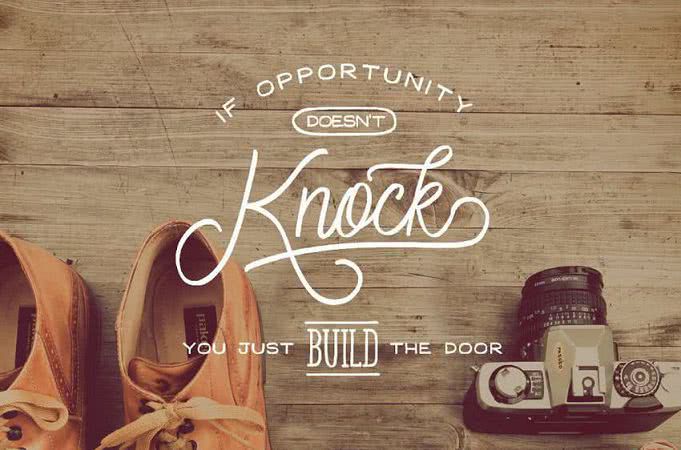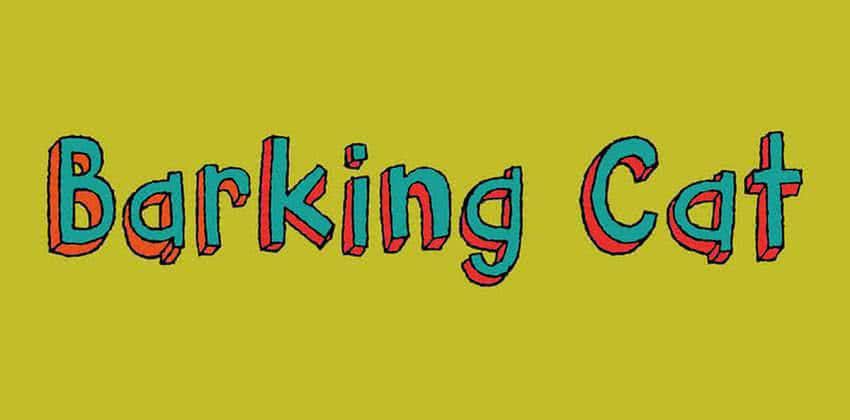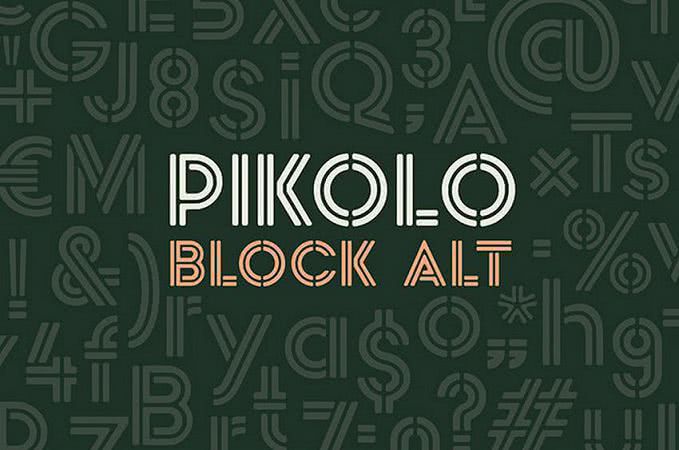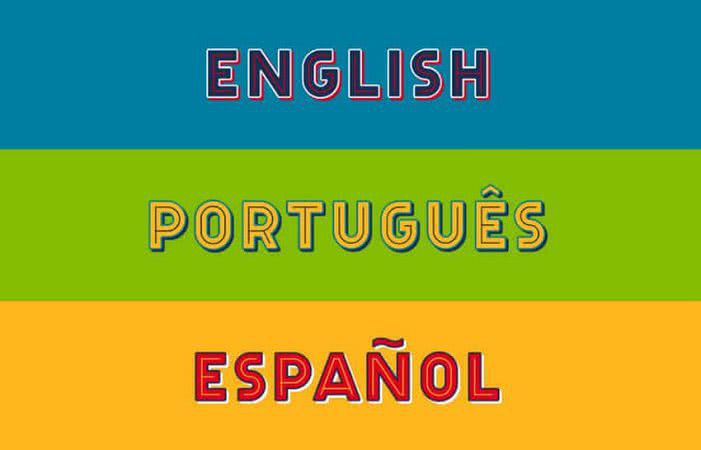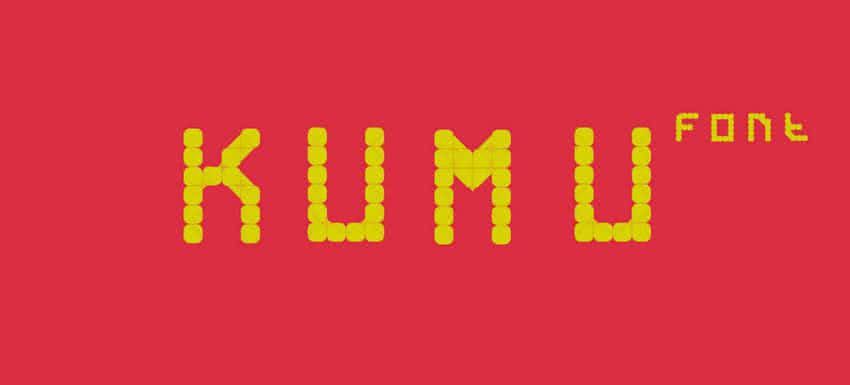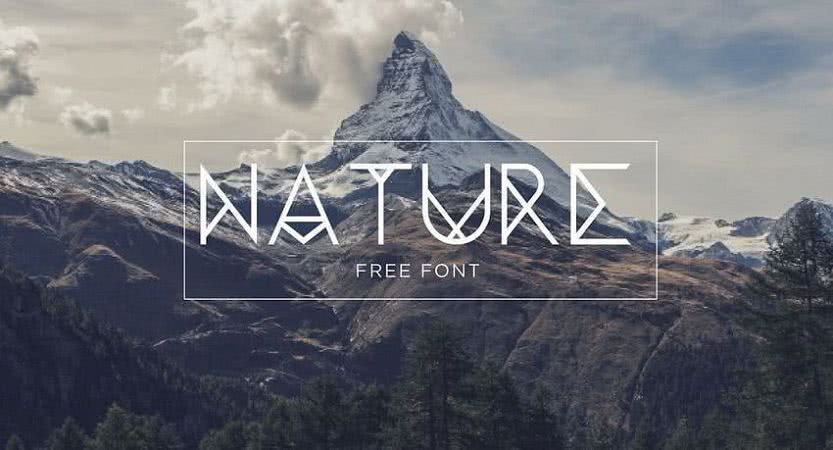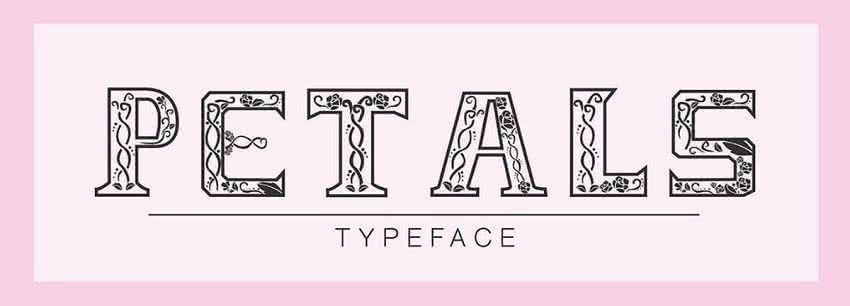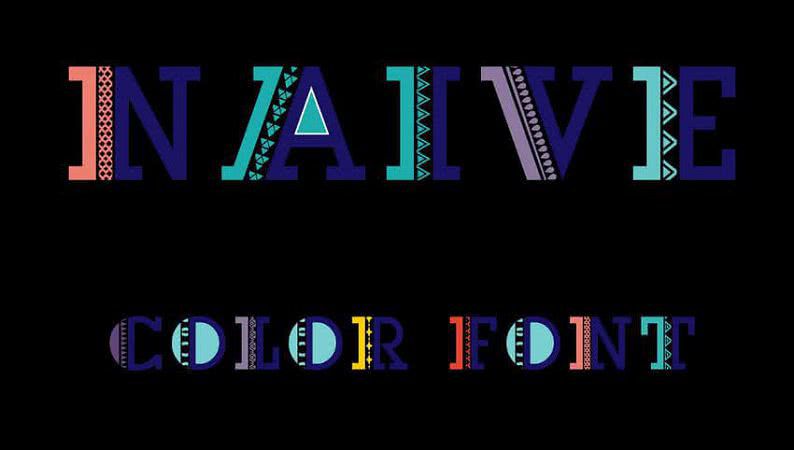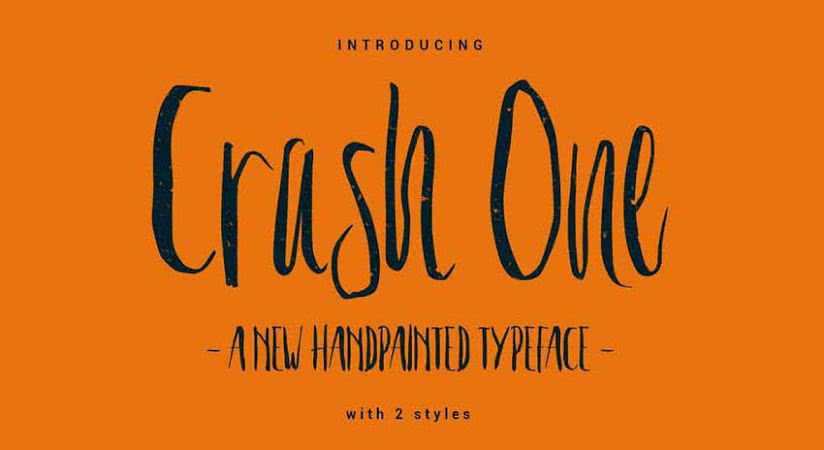
Картинка стоит тысячи слов. Мы все знаем, что изображение может быть очень описательным, но, нравится нам это или нет, мы не можем создавать дизайн без текста. Только с помощью слов мы можем быть уверены, что читатели получат точное сообщение. Это не означает, что мы прилипли к простому тексту; современные шрифты позволяют превратить простую надпись в произведения искусства.
Предположим, что вам нужно создать логотип в винтажном стиле; попробуйте старинный шрифт, такой как Vhiena, который включает в себя семь стилей для смешивания и соответствия. Или, может быть, вас попросили воссоздать ультрасовременную атмосферу, тогда вы можете сделать это с помощью шрифта, такого как Quantum, который имеет заглавные буквы с футуристической привлекательностью.
Vhiena
Quantum
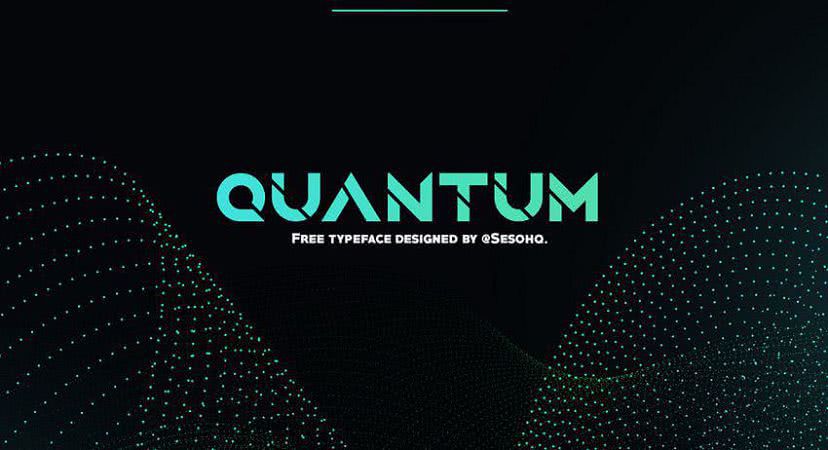
Нынешнее состояние типографики очень перспективно. От элегантных каллиграфических шрифтов, таких как SPIRITED FONT SET, до деревенских, таких как Barking Cat, шрифты могут быть всех форм, стилей и дизайнов.
SPIRITED FONT SET
Barking Cat
Разнообразие стилей поистине впечатляет. В то время как премиум-категория богаче, чем бесплатные шрифты, количество вариантов может вас удивить.
Учитывая современные тенденции, художники-типографики дарят нам новые решения. Пока что 2018 год находится под эгидой геометрии и высокотехнологичной атмосферы. Если вы хотите следовать тенденциям, вы должны обратить внимание на Pikolo Block Alt, Celebration, Kumu и Nature — эти бесплатные шрифты прекрасно справляются с этой задачей.
Pikolo Block Alt и Celebration — это два шрифта, которые имеют много общего. Они получают свою красоту из линейного искусства. Оба имеют заглавные и строчные буквы, цифры, символы и общие стилистические лигатуры. Используйте их для создания логотипов, заголовков или баннеров.
Pikolo Block Alt
Celebration
Каждый символ в Kumu — это гармоничное сочетание относительно больших точек. Шрифт выглядит немного деревенским, но он идеально подходит для восполнения брутальных проектов. Он охватывает общий набор символов.
Kumu
В отличие от предыдущих примеров, Nature умело сочетает геометрические детали и элегантные формы букв, что приводит к великолепному, изысканному шрифту. Его харизма идеально подходит для современного дизайна. Он состоит из заглавных и строчных букв и цифр.
Nature
Если вас не интересуют тенденции, вы всегда можете попробовать художественные или оригинальные решения. В нашем списке есть несколько шрифтов, которые придадут вашему дизайну индивидуальности.
Художественные шрифты
Художественные шрифты предназначены для добавления харизмы и творческой атмосферы. Рассмотрим Petals, Naive Color Font и Crash One.
Название шрифта Petals говорит само за себя. Он инкрустирован красивыми розовыми деталями, которые обеспечивают каждому символу прекрасную женскую ауру.
Petals
Naive Color Font — дерзкий, запоминающийся и эксцентричный. Его геометрическая атмосфера приятно подавляющая. Его можно использовать только для отображения заглавных букв, цифр и основной пунктуации.
Naive Color Font
Crash One — веселый и причудливый. С аутентичными кривыми рукописных форм он источает игривую харизму. Он состоит из всех распространенных букв, цифр, лигатур и знаков препинания.
Crash One
Оригинальные шрифты
Оригинальные шрифты идут рука об руку с художественными с одним небольшим отличием – они предпочитают держаться подальше от проторенной дорожки. Будучи смельчаками, эти экспериментальные шрифты удивляют своим необычным внешним видом. Рассмотрим два интересных примера: Fixer и Hawaiian Kids. Fixer — это универсальная многослойная система шрифтов, которая включает в себя семь стилей, которые вы можете комбинировать любым способом.
Fixer
Что касается Hawaiian Kids, первое, что приходит на ум, когда вы видите это: «Кто живет в ананасе на дне океана?» Вдохновленный любимым мультсериалом Nickelodeon про Губку Боба, шрифт выглядит комичным и веселым
Hawaiian Kids
Веб-Шрифты
Три стипендиата из W3C разработали WOFF (Web Open Font Format) в 2009 году, что делает его знаковым годом для веб-дизайна. WOFF изменил наше видение типографики для веб-сайтов, включая возможности использования необычных шрифтов. Рассмотрим Coral Reef Font. Этот шрифт идеально подходит для различных печатных проектов. Поставляется в WOFF, его можно легко использовать в веб-приложениях и он отлично смотреться на разных устройствах.
Coral Reef Font
Еще одна интересная вещь заключается в том, что есть множество конвертеров, которые позволяют использовать любой шрифт, например, Coco. Этот красивый шрифт имеет тонкие формы букв и доступен в стандартном OTF. Он идеально подходит для элегантного дизайна.
Coco
Последнее, но не менее важные: PSD и Wireframe шрифты
Эти два типа шрифтов не похожи на другие. Они особенные. Шрифты PSD невероятно творческие, а шрифты wireframe слишком упрощены.
Первый служит декоративным инструментом для преобразования регулярных заголовков в произведения искусства. Есть только один незначительный недостаток: нужно составлять буквы символ за символом. PSD шрифт Bright Calligraphy, Neon and Adan Font являются тремя представителями этого вида. Давайте взглянем на них поближе.
В шрифте Глеба Гуральника есть слияние металлического чувства и элегантная каллиграфия, которая приводит к выдающемуся шрифту. Набор состоит из 81 символа, охватывающего прописные и строчные буквы, цифры и знаки препинания. Каждый имеет свой собственный слой.
Bright Calligraphy
Neon выглядит урбанистическим и игривым. Стеклянные и блестящие поверхности с похожими на щетку штрихами и великолепной расцветкой формируют красивый шрифт, который идеален для показа табличек или лозунгов. Автор также предлагает пакет шаблонов в качестве бонуса, чтобы сделать ваши проекты завершенными.
Neon
Adan — это двойной шрифт, который позволяет использовать пару тонов для создания оригинальных дизайнов заголовков. Он поставляется в формате AI.
Adan
Бесплатные wireframe шрифты – это нейтральные шрифты, которые напоминают Lipsum. Они используются для завершения прототипа, разграничения текстовых областей и заголовков. Рассмотрим Flow от Дэна Росса. Он позволяет создавать абстрактные заполнители, оставляя все остальное воображению.
Flow by Dan Ross
Вывод
Каждый год приносит своих фаворитов. В 2018 году мы увидим, как будут работать геометрические шрифты. Они прекрасно дополняют популярные высокотехнологичные интерфейсы. Однако не ограничивайте себя только модными вариантами; художественным шрифтам, таким, как PSD шрифты, также есть что показать.